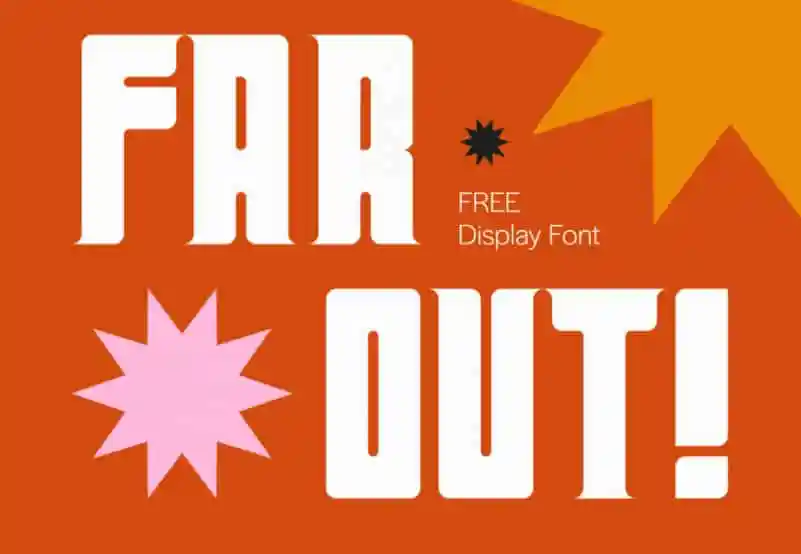
Far Out! Display Font é uma elegante e poderosa fonte feita à mão para uso em headlines e aplicações visuais criativas. Seu design moderno e bold, idealmente unicase, foi projetado para criar impacto visual e emocional. Este tipo de serif é perfeito para aplicações que valorizam um estilo retrô contemporâneo. É ótimo para uso em redes sociais, headlines, grandes-formatos impressos, editoriais, marcas, posters, designs de moda e websites — tudo o que busca confiança e aproveitamento máximo. Sem dúvida tem personalidade! Far Out! Display Font é uma escolha perfeita para quem quer destacar-se na internet ou em qualquer meio onde as grandes letras têm um impacto significativo.